아스팔 아이덴티티 디자인 : 유서 깊은 브랜드에 상큼함을
1728년부터 사과주 제조업이 가업으로 8대째 전해 내려옴. 사과와 퀄리티에 집착하며 새로운 영국의 성공 스토리. 하지만 이들의 브랜드는 고루하고 비일관적으로 응용되고 있었다. 우리가 실제로 만난 일하는 사람들의 활발함과는 어울리지 않았다. 우리는 참된 아스팔 브랜드를 만들고 싶었다.
아스팔(ASPALL) 아이덴티티 디자인 : 유서 깊은 브랜드에 상큼함을
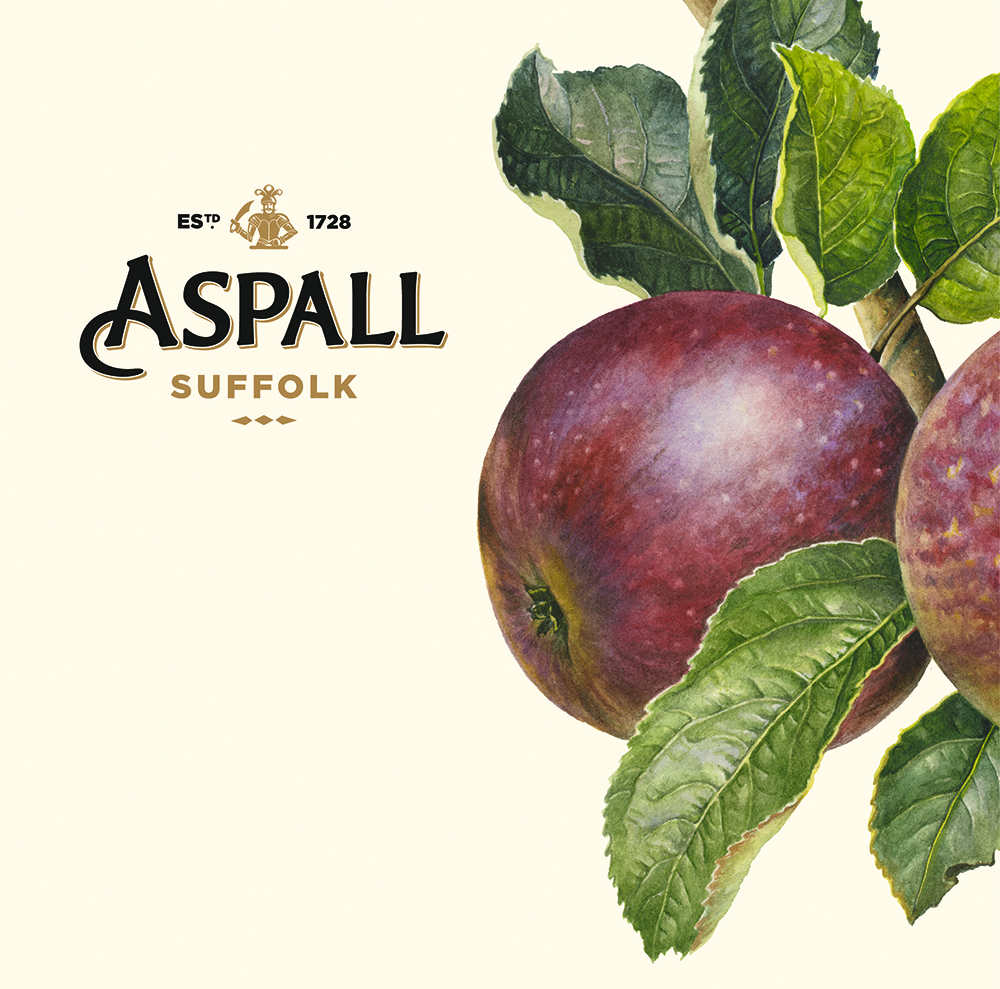
우리에게 주어진 과제는 진정성 있는 장인의 브랜드를 새롭게 하여 영국의 동시대적인 고전처럼 행동하는 브랜드로 만드는 것이었다. 트위터 피드에서 우리는 140자 안에 설명이 끝나는 완벽한 포지셔닝을 하나 찾아냈다.
‘@아스팔: 서퍽주에서 1728년부터 사과주 제조업이 가업으로 8대째 전해 내려옴. 사과와 퀄리티에 집착하며 새로운 영국의 성공 스토리’
배리와 헨리 슈발리에(Barry and Henry Chevallier), 두 형제가 이 회사를 운영하고 있는데 이들은 클레멘트 슈발리에(Clement Chevallier)가 1728년에 정한 기준을 아직도 좇고 있다. 하지만 이들의 브랜드는 고루하고 비일관적으로 응용되고 있었다. 우리가 실제로 만난 일하는 사람들의 활발함과는 어울리지 않았다. 우리는 참된 아스팔 브랜드를 만들고 싶었다. 이것은 아름다운 아이덴티티를 가질 자격이 있는, 영국의 고전적인 장인정신을 갖춘 브랜드였다.
아이덴티티 전체가 하나로 모이는 지점은 제품의 라벨이었는데 해결해야 할 기술적 디자인 이슈가 몇 가지 있었으므로 근본적으로 모든 각각의 요소들을 떼어내고 이것들을 말끔하게 정리하여 다시 모아 놓았다. 하지만 어떤 디자이너라도 첫 번째 소임은 탐정 역할이다. 내게는 아스팔 홀의 아카이브에서 오래된 서류와 기록들의 먼지를 불어 날려버리고, 옛날 마크, 모티프, 사진들을 발굴해내는 작업으로 즐겁게 뛰어드는 일이었다.
※ NB스튜디오가 사과주 제조사 아스팔을 위한 새로운 아이덴티티 제작과정을 단계별로 설명한다.
01 — 법의학적 연구
우리는 맡은 바를 부지런히 수행해, 제품 세트의 조사와 함께 로고가 나타난 지점을 연구했다. 우리는 워드마크의 다양한 변형을 찾아냈으며 많은 서체들을 발견했다. 그러고 나서 힌트가 될 참된 자산을 찾기 위해 아카이브를 뒤졌다.
02 — 컨셉 개발
우리의 초기 아이디어 일부는 솔루션에까지 반영되었다. 아카이브에서 진정성 있는 아이덴티티의 소스를 찾은 것이다. 사과주를 샴페인인 것처럼 대하는 것, 우리가 ‘사과 짜내는 기계가 인쇄출판업을 만난 것’이라고 부른 서체 위주의 컨셉을 만들어내는 것이었다.
03 — 분석
오래된 워드마크의 P와 A에는 특징이 있었으나, 문제점도 있었다. A의 돋보이는 장식적 부분은 개성을 더했으나 사용하기 어렵게도 했고, A와 S 사이의 공간도 너무 많았다.
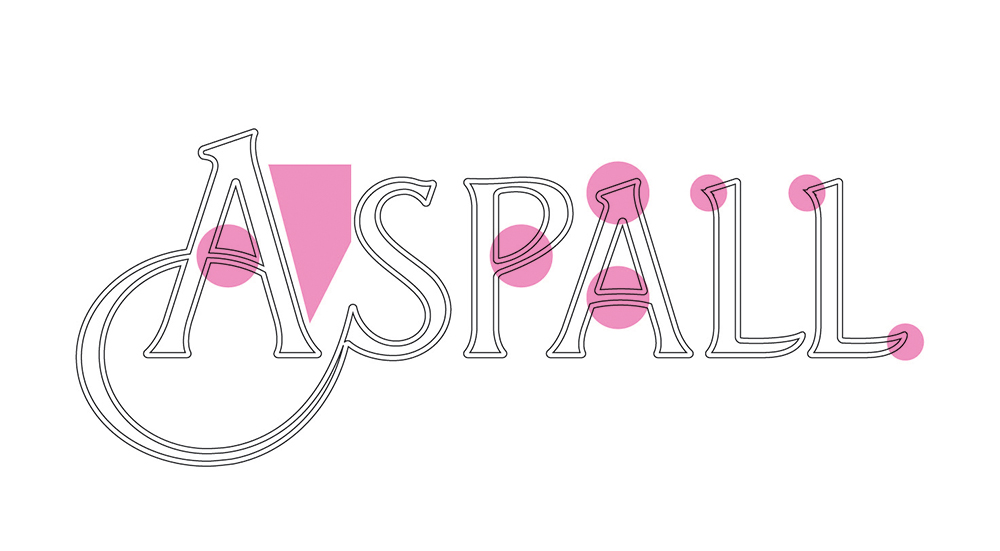
04 — 영감을 얻다
우리는 세인트브라이즈 인쇄 · 출판물 도서관에서 장식 활자들, 합자들, 기타 별난 것들을 탐색하며 시간을 보냈다. 그런 다음에 느슨하게 워드마크를 다시 그리고, 뚜렷이 구별되는 모든 것을 유지하되 더 낫게 만들었다.
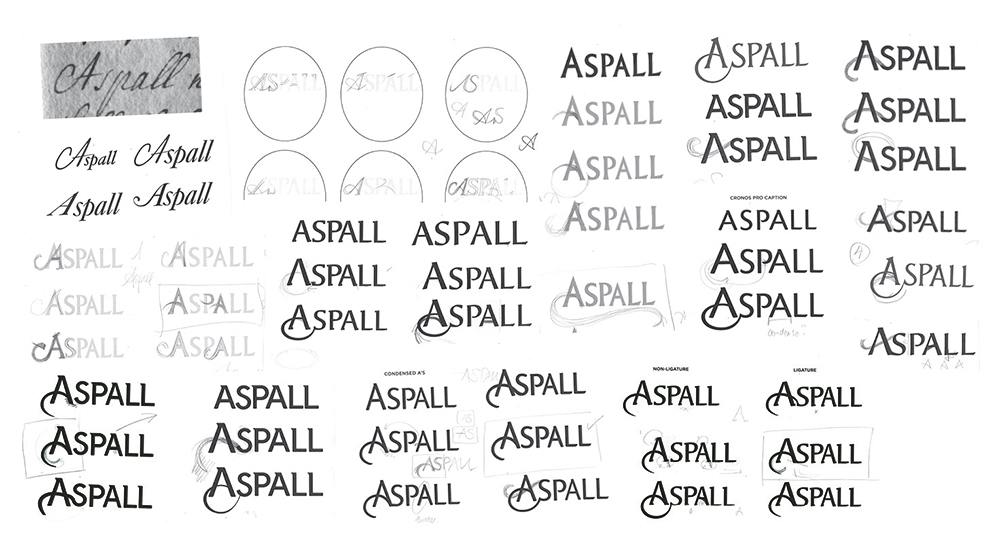
05 — 개발
우리가 발전시킨 버전은 더 캘리그래피적이고 상형 문자와 같다. 크기가 조정된 첫 글자 A에는 장식된 야단스런 요소가 돋보인다. A의 크로스바에 통일감을 주었고, 각진 세리프를 더했으며 L의 곡선을 들어올렸다.
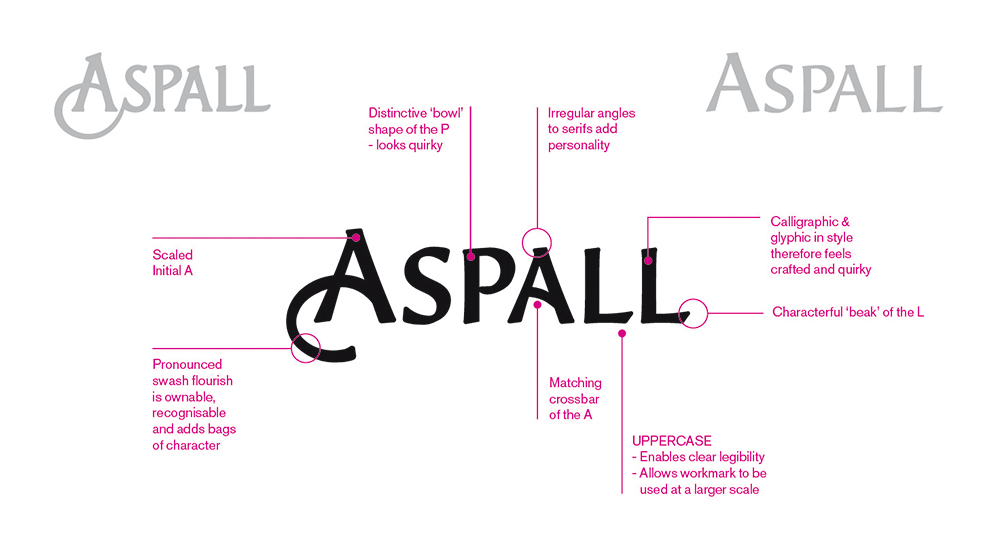
06 — 일러스트레이션 수정
이전 버전의 기사 심볼은 공예가의 손을 타지 않은 것처럼 보였다. 브랜드 정신을 더 구현할 수는 없을까? 일러스트레이터 크리스토퍼 워멜(Christopher Wormell)이 다듬은 우리의 버전은 기사가 자리 잡고 있는 원래의 조각상을 참고로 한 것이다.
07 — 2차 모티프
사과는 아스팔의 핵심이다. 우리는 식물 일러스트레이터인 로지 샌더스(Rosie Sanders)가 그린 특별한 회화 컬렉션을 연구했다. 우리의 클라이언트만큼이나 사과에 푹 빠진 사람을 찾은 것은 기쁜 일이었다.
08 — 모두 한데 모으기
서퍽주 풍경의 정신을 전하는 색상 팔레트, 설립자와 가족을 그려낸 목판물, 지역 토속 전통에 뿌리를 둔 목소리 톤 등도 살펴보았다.
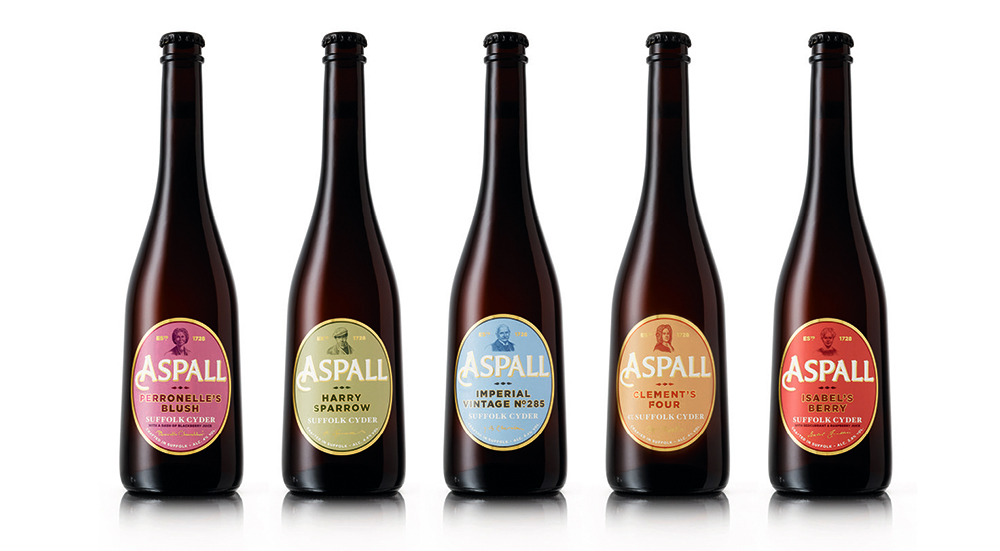
09 — 새 로고
리디자이된 새로운 로고는 아스팔의 역사적 유산에 민감하며 제품들의 진정성을 강조하고 있다. 건전한 원칙들은 장차 사과주 변형이 자라날 수 있는 하나의 플랫폼을 제공하며 이 변형에는 아스팔 식초 라인과 신제품 개발 등이 포함된다.